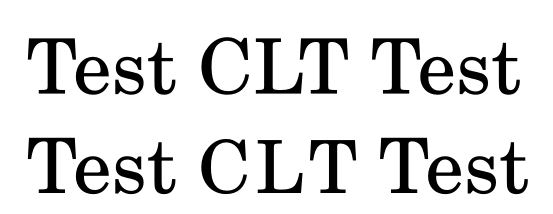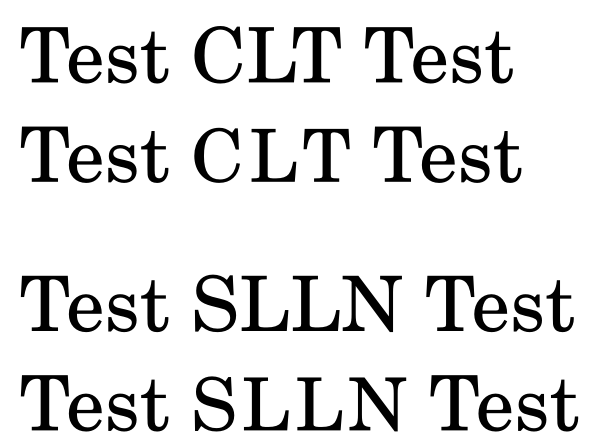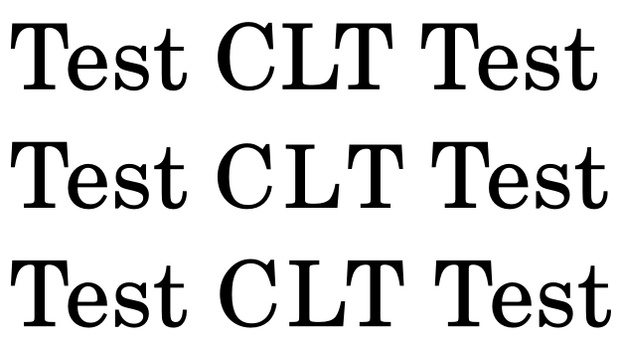
Sperren o. ä. bei Abkürzungen?
nachdem ich nun all meine verwendeten Abkürzungen ("z. B.", "d. h.", "i. i. d.", ..) dahingehend korrigiert habe, dass kein Leerzeichen, sondern ein Spatium als Wortzwischenraum steht (siehe typokurz), stellt sich mir eine weitere Frage.
Nun gibt es bei uns aber noch Abkürzungen wie CLT (engl. central law theorem) oder SLLN (engl. strong law of large numbers) und ich frage mich, wie man solche Abkürzungen korrekt setzt. Ich betone, dass ich sie nicht in Kapitälchen gesetzt habe, möchte aber fragen, ob es dennoch etwas zu beachten gibt.
Wenn Du die Abkürzungen in Versalien läßt, dann solltest Du einfach (leicht) spationieren, wie das generell bei Versalien gute typografische Praxis ist. Spatien braucht man bei derartigen Abkürzungen natürlich nicht. Warum auch? Wenn Du zusätzlich noch die Versal-Abkürzungen etwas besser in den Fließtext integrieren möchtest, dann kannst Du sie um 0.5 bis 1 pt verkleinern (m.E.n. eher 0.5 als 1).
Ist es das was Du wissen wolltest? :-?
Danke erstmal. Ich habe eben erst bemerkt, dass mein erster Satz völlig sinnlos war und habe ihn mal korrigiert. :oops:
Aber ja, das dürfte so ziemlich die Antwort auf meine Frage sein. Sollte man dann sowohl leicht spationieren, als auch verkleinern, oder sich lediglich auf eine der beiden Varianten beschränken?
Beides zusammen sorgt dafür, daß sich die Versalien besser in das Gesamtbild des Textes einfügen. Ich persönlich empfinde hier die Verkleinerung als etwas wichtiger als die Sperrung, am schönsten ist es aber wenn beides gemacht wurde. :roll:
ich habe es jetzt mal 0.5pt kleiner gesetzt und eine 0.06em-Spationierung eingefügt (darüber zun Vergleich wie die umgebende Schrift gesetzt). Wie sieht es in deinen Augen aus?
[...] die Verkleinerung als etwas wichtiger als die Sperrung [...]
:-o
Wie sieht es in deinen Augen aus?
Da muss zwischen C und L noch Luft: momentan hängen die noch aneinander, und das T steht ganz allein und ist traurig ... :cry:
Danke. Also sogar unterschiedlich spationieren. Ich sehe schon, mir fehlt (noch?) der Blick für sowas. Hier nun eine Spationierung von 0.07em und 0.06em. Ebenfalls hänge ich gleich das modifizierte "SLLN" an.
Da muss zwischen C und L noch Luft: momentan hängen die noch aneinander, und das T steht ganz allein und ist traurig ... :cry:
Für Überschriften vielleicht, aber im Fließtext würde ich nun wirklich die Kirche im Dorfe lassen. Dort Einzelbuchstabenausgleich zu machen ist m.E. völlig übertriebener Aufwand.
Und was das Ausgleichen angeht: geht Dir das nicht so? Versal-Abkürzungen im Fließtext sehen immer zu groß aus und das stört zumindest mich deutlich mehr als die zu eng stehenden Buchstaben. Das fällt zumindest meinem Auge nicht so auf weil die Kleinbuchstaben ja quasi »den gleichen Abstand haben«, wenn Du verstehst was ich meine. Der unpräzise Umriß der Versalabkürzungen paßt sich da weniger an. Aber das mag nur meinen persönlichen Eindruck repräsentieren.
Für Überschriften vielleicht[..]
Wo du es ansprichst: Zumindest das CLT steht auch in einer Überschrift (primär aber im Fließtext). :-D
Also sogar unterschiedlich spationieren. Ich sehe schon, mir fehlt (noch?) der Blick für sowas.
Für Überschriften vielleicht, aber im Fließtext würde ich nun wirklich die Kirche im Dorfe lassen. Dort Einzelbuchstabenausgleich zu machen ist m.E. völlig übertriebener Aufwand.
Hmnjanaja ... Ist auch vielleicht mein ganz persönlicher Fetisch ... ;-) Aber für mich ist es wirklich ganz essenziell, dass Versalien gesperrt gehören ... Und ausgeglichen :-D Im Fließtext ist das so eine Sache ... In Wirklichkeit gehören da ja Kapitälchen hin: dann reicht auch leichtes Sperren, ausgleichen muss man die dann (im Fließtext) nicht mehr, um vor meinem Auge Gnade zu finden ... ;-)
Aber wenn man in dem Text nur drei, vier solche Dinger hat, und unbedingt Versalien nehmen will ... Die lassen sich ja mit Copypaste verpflanzen, wenn sie mehrmals auftauchen ... :-)
Und was das Ausgleichen angeht: geht Dir das nicht so? Versal-Abkürzungen im Fließtext sehen immer zu groß aus und das stört zumindest mich deutlich mehr als die zu eng stehenden Buchstaben. Das fällt zumindest meinem Auge nicht so auf weil die Kleinbuchstaben ja quasi »den gleichen Abstand haben«, wenn Du verstehst was ich meine. Der unpräzise Umriß der Versalabkürzungen paßt sich da weniger an. Aber das mag nur meinen persönlichen Eindruck repräsentieren.
Doch, aber da gehören ja auch in den meisten Fällen Kapitälchen hin ... ;-) Und Versalien verlieren auch ganz gehörig an Schrecken, wenn sie erst mal sauber spationiert und gesperrt sind, sticht gleich viel weniger ins Auge :-D Oder, andersrum gesagt: die Versalien fallen nicht nur wegen ihrer Größe auf, sondern auch wegen dieser Zusammenballung von Schwarz, die sich durch Ausgleich und Spationierung eben ne ganze Ecke auflöst ... :-D
Ups, der Minimalist war schneller! Ja, an das Setzen in Kleinbuchstaben und das anschließende Umschalten hatte ich nicht gedacht. :bow:
Lach, eine Endlosschleife. ;-)
Nachtrag: Also es ist natürlich "CLT" in Kapitälchen. "Clt" in Kapitälchen setzen sieht anders aus, würde sich mir der Sinnhaftigkeit aber entziehen, da es nunmal CLT und nicht Clt heißt.
Was Du möchtest ist aber »clt«, weil Du dann Versalien hast, die so klein sind wie die Kleinbuchstaben im umgebenden Text (eigentlich nen Tick größer) und die genau passende Strichstärke haben :-D